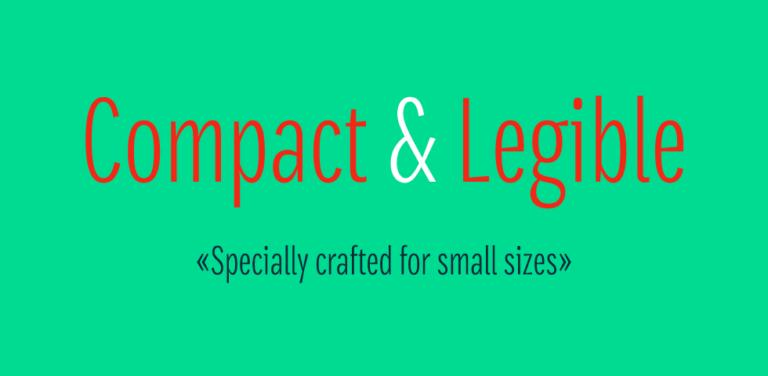
Densia Sans字体(Densia Sans)
Densia Sans是一种经济的无衬线字体,设计用于6至14点的尺寸。 它的高x高和窄的宽度使它在每个空间非常有限的时候都能发光。 不仅节省空间,Densia Sans还提供了820套雕文,包括小型大写字母,区分大小写的形式,比例和表格形式,上级,下级和分数。 这是免费的个人和商业用途。